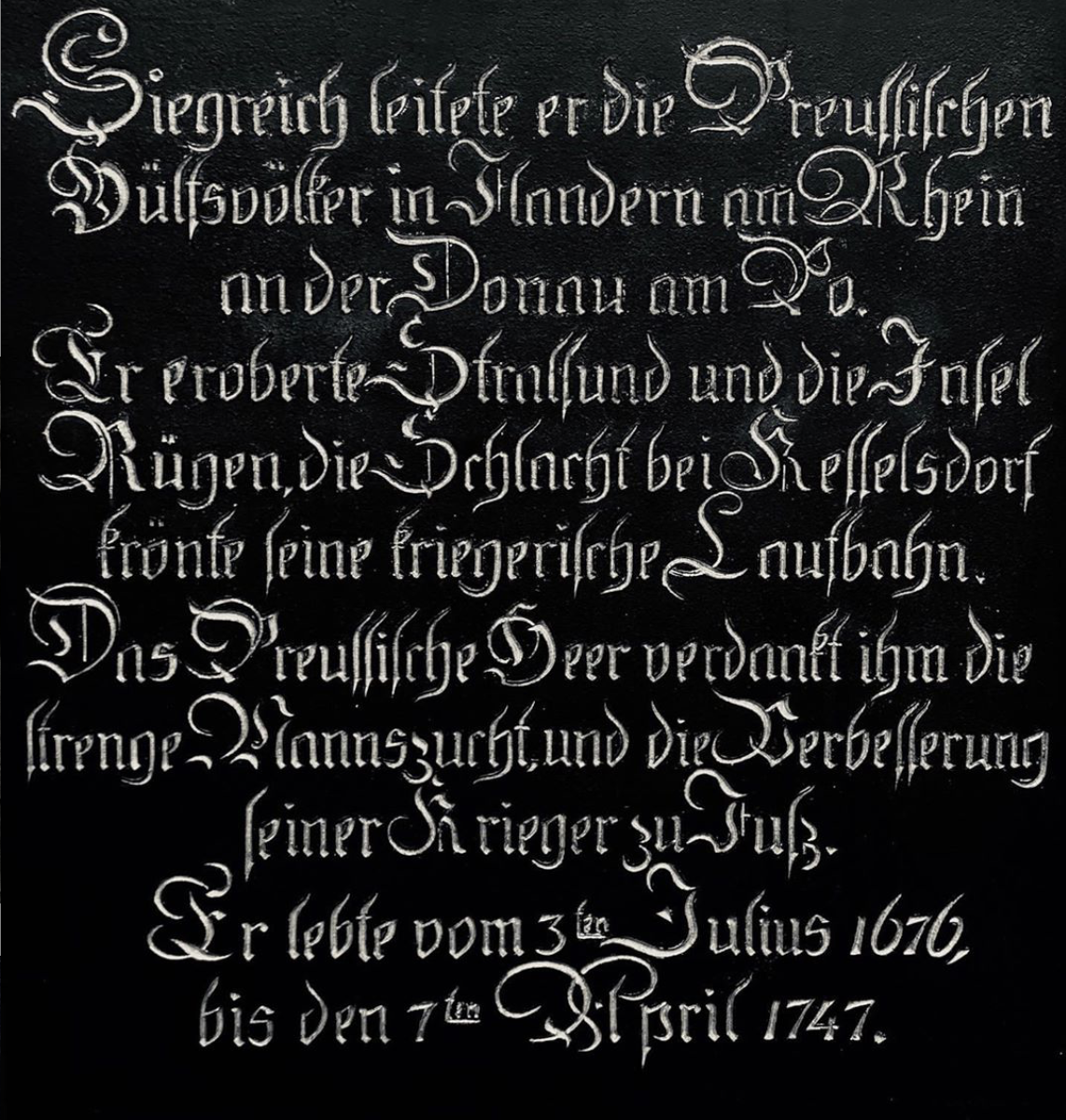
Suche nach einer Humanistische Minuskel, warscheindlich 18. Jh
Ich bin auf der Suche nach einer alten humanistische Minuskel. Gibt es diese vielleicht als otf? irgendwo? Ich bin auf die Monarchia gestossen, was aber nicht sein kann.
Denkst du es gibt keine digitale Version davon? Das die irgend jemand nach gezeichnet hat?
Hast du dich denn schon durch Schriften von Gerhard Helzel gearbeitet? War da nichts dabei?
Mein lieber Scholli, ich hätte ja noch gerne die eine oder andere Fraktur gemacht, aber der Herr Helzel hat sie schon alle durchgenommen :-?